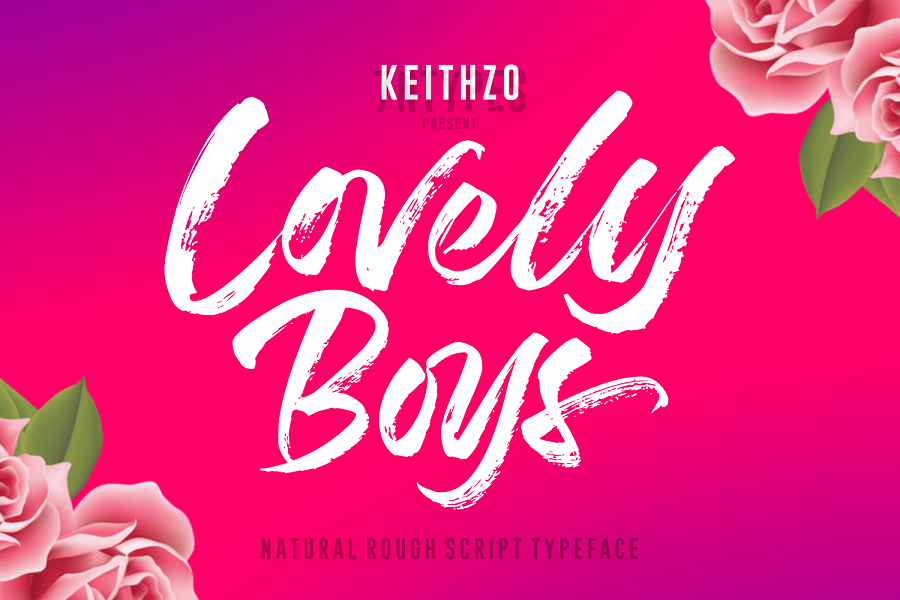
Lovely Boys Brush Font – Fonte Grátis
Lovely Boys Brush Font
Olha quem tem uma novidade inspiradora para você! Inspirada na tipografia natural com esfincionadas, a font Lovely Boys Brush é a escolha perfeita para quem busca um estilo fresco e despojado. Esta font script foi escrita em movimentos rápidos usando um pincel de letra bem seco. Ela combina uma aparência natural e irregular com uma presença poderosa, tornando-a uma opção ideal para qualquer projeto que você estiver criando. Lovely Boys Brush Font é um belo exemplo deste estilo, desenvolvida e compartilhada pelo designer Keithzo (7NTypes). Além de oferecer letras maiúsculas e minúsculas, ela ainda inclui grandes conjuntos de aviões internacionais, números e diversas línguas, tornando-a perfeita para trabalhos multilingues. Este é um verdadeiro presente para todos os amantes do design gráfico que estão buscando uma fonte script com uma aparência única e autêntica. Descubra o poder de Lovely Boys Brush Font em qualquer projeto! É a escolha certa para trazer uma pegada fresca e distintiva ao seu trabalho. Seja na criação de logotipos, design editorial ou até mesmo como fonte para mensagens multilíngues, esta font traz um toque autêntico e despojado aos seus trabalhos. Descubra mais sobre Lovely Boys Brush Font e descubra por que ela se tornará uma das suas preferidas!